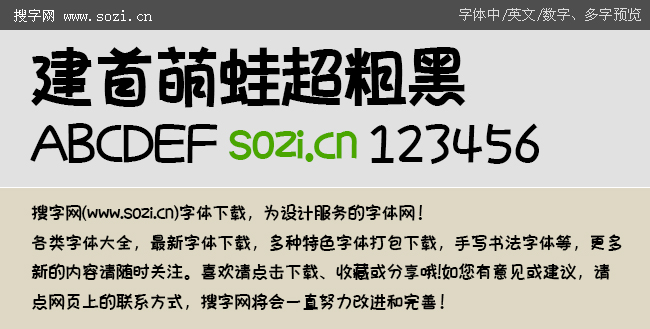
建首萌蛙超粗黑
搜字網(wǎng)提供一款建首萌蛙超粗黑中文字體下載,建首萌蛙超粗黑是一套卡通風(fēng)格的POP字體。字體筆畫粗壯醒目,字形為卡通風(fēng)格,充滿童趣,看上去非?蓯(ài)。適合兒童包裝設(shè)計(jì)、海報(bào)設(shè)計(jì)、廣告設(shè)計(jì)等應(yīng)用。